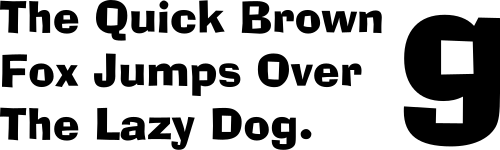
| カテゴリ | 画面 |
| デザイナー | フリーマン・クロウ |
| 鋳造所 | ATF |
| リリース日 | 1961 |
アドリブは、 1961年にフリーマン・クロウがアメリカン・タイプファウンダーズのためにデザインした装飾的な書体です。1960年代前半から中期にかけて非常に人気があり、今日でもその時代を思い起こさせるものとしてよく使われています。[検証失敗] [1]
この書体は、60 年代風の四角いカウンターで知られています。このフォントの SoftMaker バージョンでは、グリフのエッジがより直線的になっています。
アドリブの使用例
Ad Lib は次のような用途で使用されています:
- フィリックス・ザ・キャットのエピソードタイトル。[疑わしい–議論する]
- 1960年代のバットマンテレビシリーズのエピソードタイトルと「Same Bat Time, Same Bat Channel」のテキストオーバーレイ
- 1971年の映画「ウィリー・ウォンカとチョコレート工場」のオーガスタス・グループの歌詞
- 1976年の映画「バッドニュース・ベアーズ」
- ピンクパンサーシリーズのタイトル、およびデパティ・フレレング・エンタープライズが1964年から1967年にかけて制作したルーニー・テューンズの短編映画のクレジット
- 1982-1983年のテレビシリーズ「ミートボール&スパゲッティ」
- 1982年のアニメ映画「グリンチ」
- アウトレイジ、既婚者のためのガイド、クルーレス、ジェイ&サイレントボブの逆襲、ダガーと呼ばれる男などの映画に出演。
- 1996-99年版「ザ・デート・ゲーム」の第1シーズンのテレビ画面のスコアとロゴに使用された。
- 1970年から1973年まで放送されたテレビシリーズ「ナイトギャラリー」のタイトル
- 1967年の映画「夜の大捜査線」と、それを原作とした1988年のテレビシリーズ
- マーシャと熊のエンドクレジット
- 「A Pup Named Scooby-Doo」と「Yo Yogi」のエピソードタイトルカード!
- ディズニーアニメシリーズ「ダークウィング・ダック」のロゴとバンコ
- 臆病犬カレッジのエピソード「どこでもない中心への旅」のタイトルカード
- ニルヴァーナのライブアルバム『From the Muddy Banks of the Wishkah』のカバー
- アニマニアックス関連商品のほとんど
- アニメシリーズ「アメリカン・ダッド」のオープニングとエンディングのクレジット。
- タイラー・ペリーのアシステッド・リビングのタイトル
- ウェブサイト「ロッテントマト」の2018年以前のロゴ
- ワームズアルティメット メイヘムまでのワームズ ビデオゲームフランチャイズ
- ニコロデオンスタジオ周辺の標識は、ネットワークの「バルーン」フォントと交互に表示される
- 1996年のMGM/UA再発版『ピーウィーのプレイハウス』のボックス
- ポケパークWii ピカチュウの大冒険、ポケパーク2 ふしぎの国のアリス、ルイージマンション3のセリフ
- ブームブロックスビデオゲーム
- 子供向け番組「マギーと凶暴な野獣」のタイトルカード
- アラウンド・ザ・コーナー時代の90年代のセサミストリートのホームビデオのエンドクレジット
- 1997年から2001年までのThe Wiggles TVシリーズとホームビデオ
- イギリスのテレビシリーズ「That'll Teach 'Em」のロゴ
- アメリカのレストランチェーンFriendly'sのソフトサーブサイクロンメニューのタイトルの一部
- サブリナ:アニメシリーズのエンドクレジット
- マイティ・マイティ・ボストンズのロゴ(アルバムのカバーにもよく使われている)
- 1999 年のChuck E. Cheeseの印刷広告
- AZ動物辞典
- ビートルズのセカンドアルバムのカバー
- 2003年のモンキーズDVDボックスセット